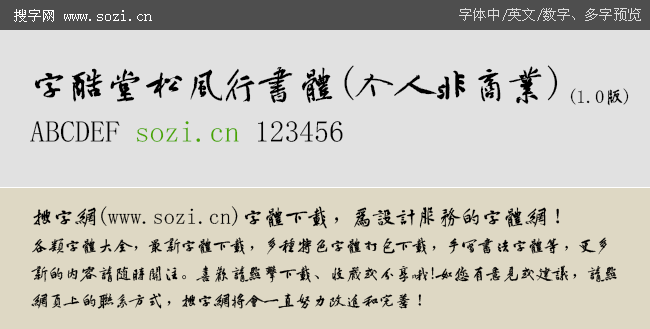
字酷堂松風(fēng)行書體(個(gè)人非商業(yè))
搜字網(wǎng)提供一款字酷堂松風(fēng)行書體(個(gè)人非商業(yè))中文書法字體下載,字酷堂明行體是一款非常漂亮的行書書法字體,字體飄逸大方,結(jié)構(gòu)合理沉穩(wěn),整體字形非常大氣,適合應(yīng)用于廣告設(shè)計(jì)、名片設(shè)計(jì)、包裝印刷、海報(bào)設(shè)計(jì)等應(yīng)用。